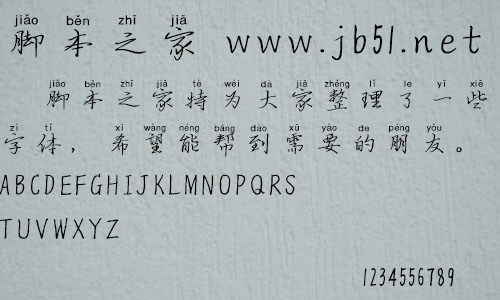
漢儀寒石拼音體簡一款不錯的藝術(shù)字體,由漢儀字庫出品,字體筆觸纖細(xì),字形流暢,支持漢字和拼音同步輸入,具有很好的視覺感,適合應(yīng)用于藝術(shù)設(shè)計、平面宣傳設(shè)計、網(wǎng)頁設(shè)計,書法字帖等領(lǐng)域,需要的朋友可以前來本站下載。